文字作为设计的一个信息载体,它要比任何图片信息都要更直观、一目了然。所以在设计工作中,字体的选择也是设计师的必修课。我们都知道字体库的数量多之又多,而每款字体所传达的视觉感受都各不相同,那么在日常的设计工作中,如何合理的使用字体,使用字体时应该注意什么?
下面我们一起来看一下使用字体应该注意的问题:
1、统一字体形式
这个点很好理解,就是作品中对应位置的字体要统一使用相同的字体,不要出现同一位置多种字体,比如:标题字体、副标题字体、说明文字字体等等,做到统一有助于提升作品档次。
2、统一字体气质
每款字体所传达的视觉感受也都不同,在使用字体时,尽量选用气质雷同的字体相互搭配,比如:标题中国风字体,那么副标题和说明性文字就尽量贴合中国风的感觉或者与标题保持一致。这样做有助于提升作品的档次以及整体性。
标题字体:字语华风手书
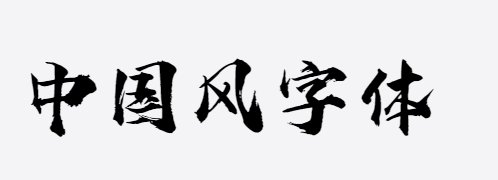
副标题字体:汉标老梁行楷
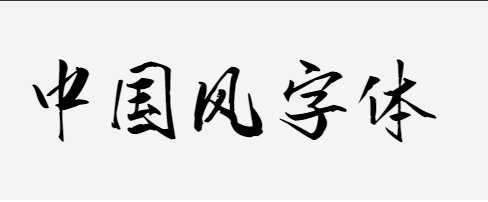
说明文字字体:X-花样美男